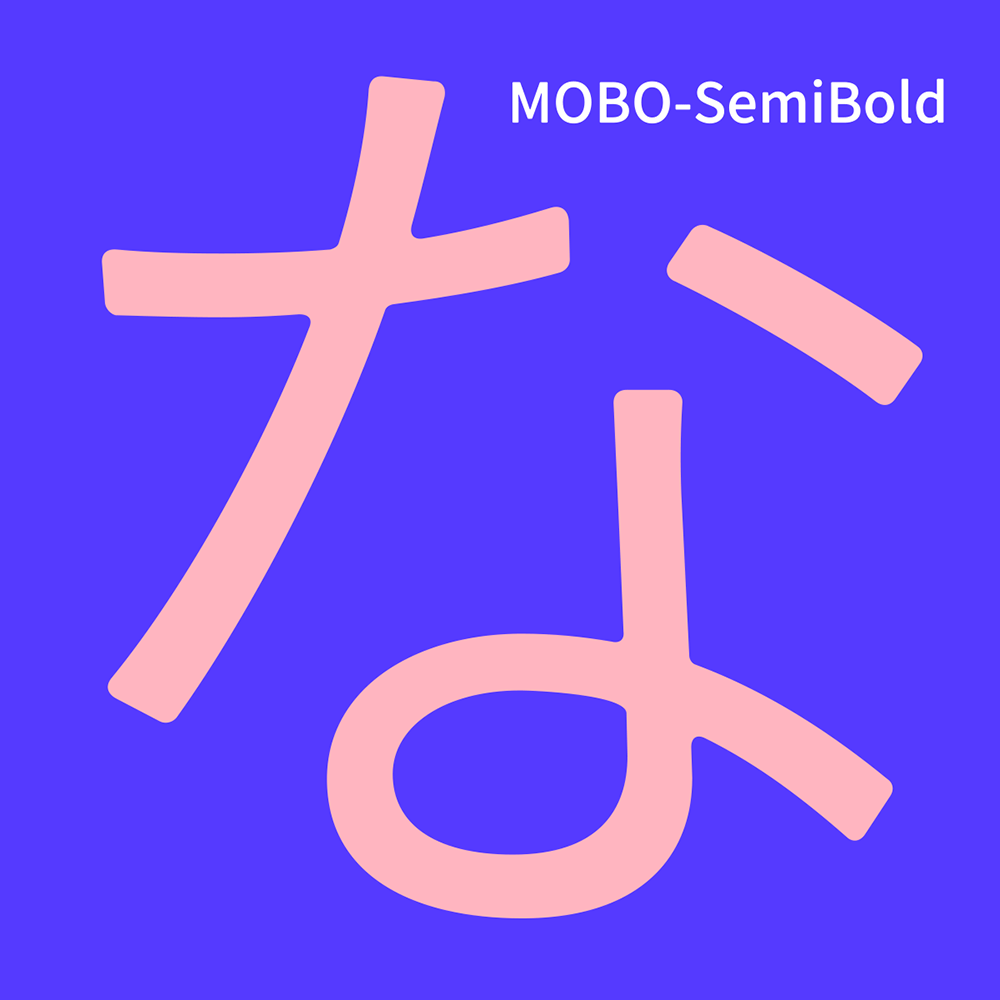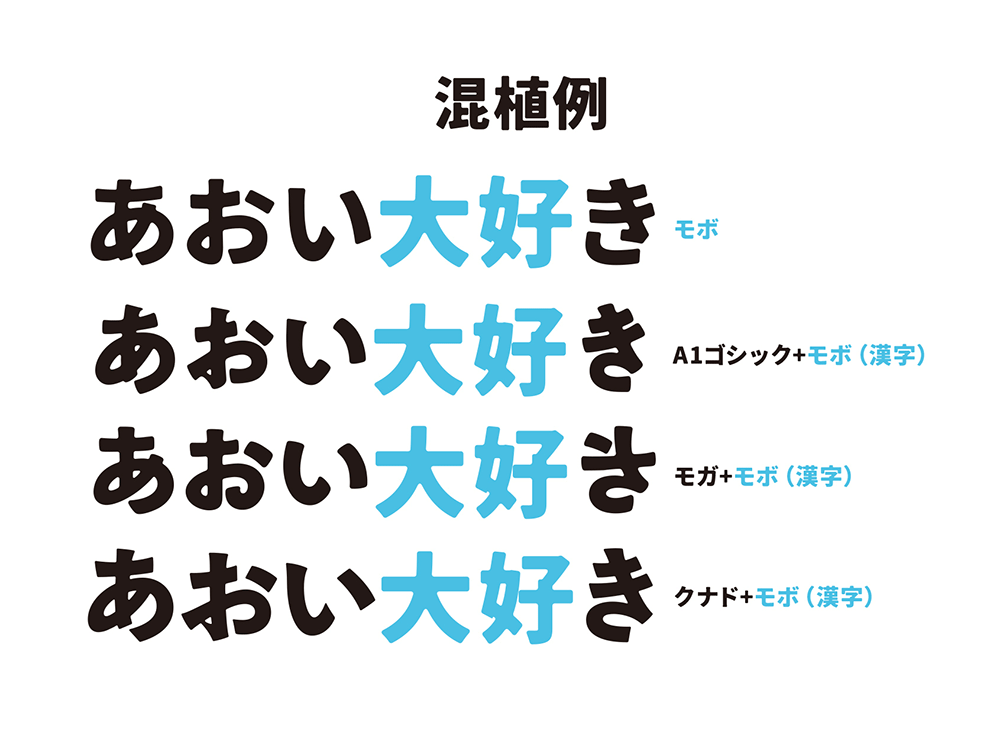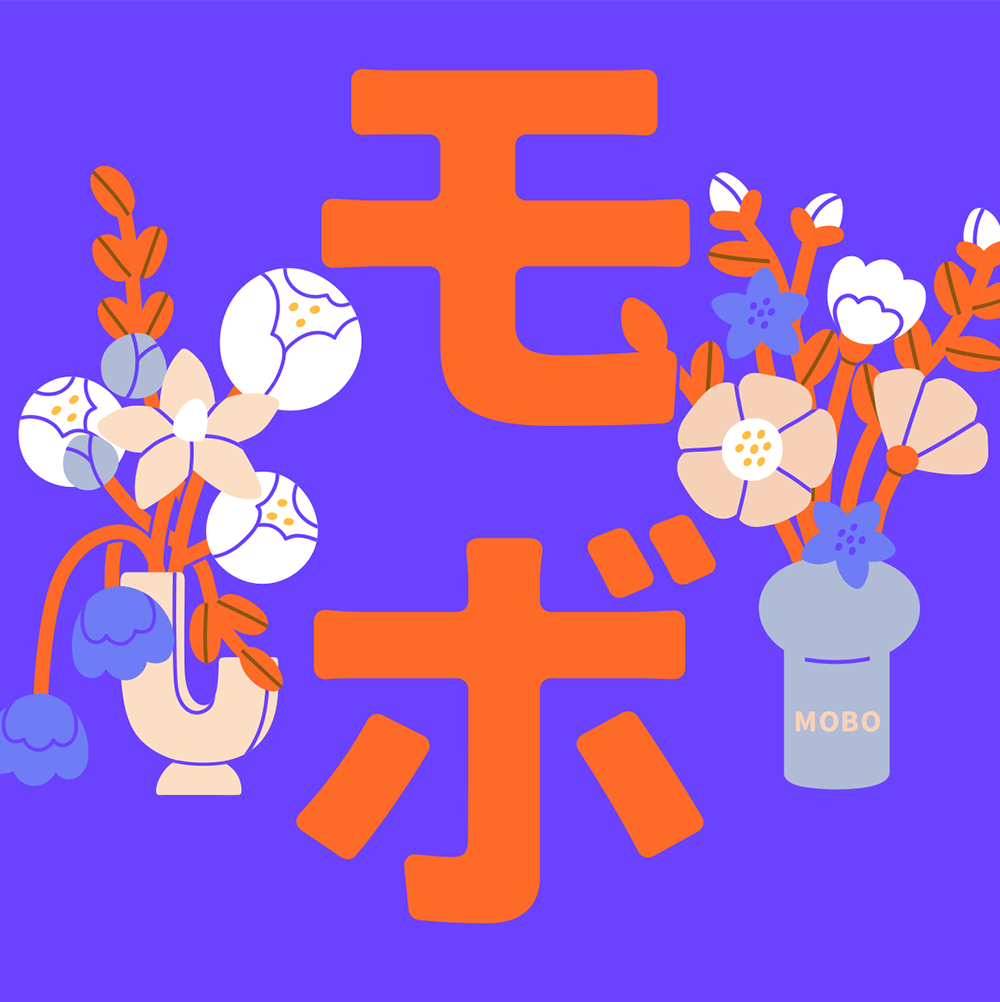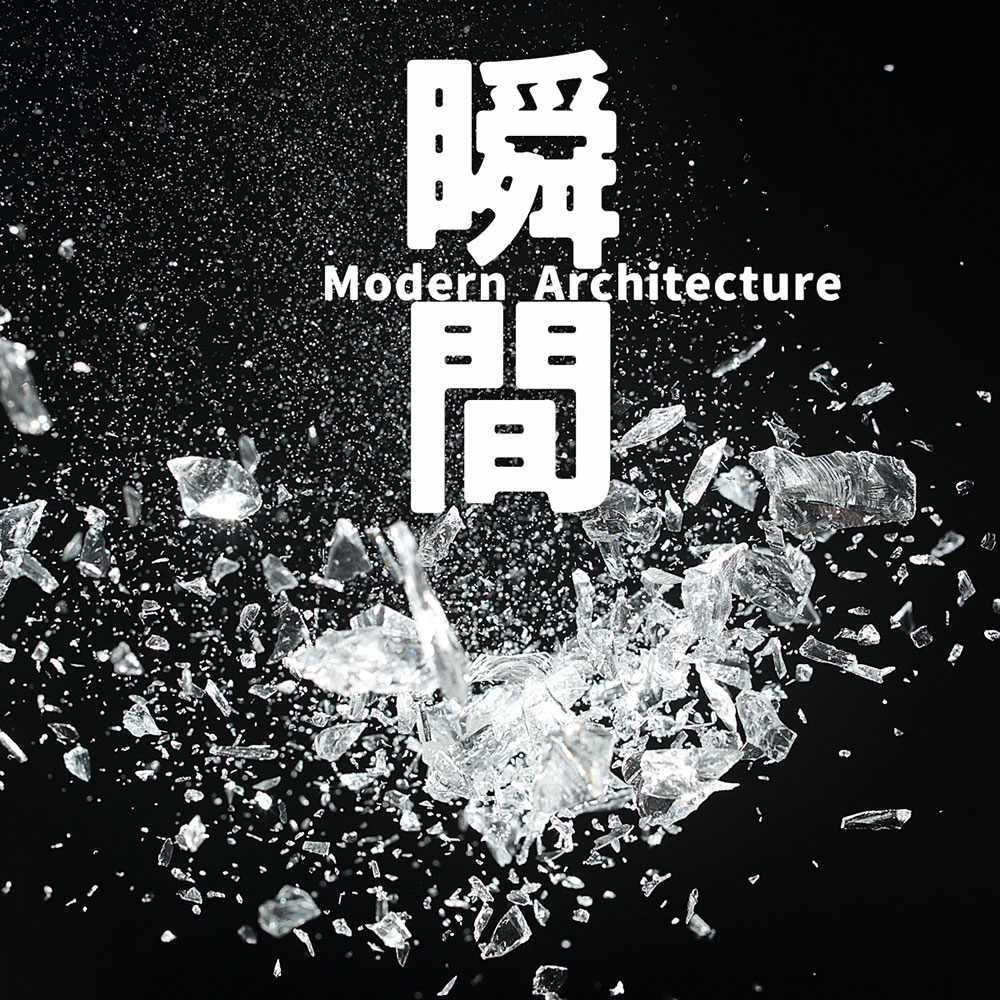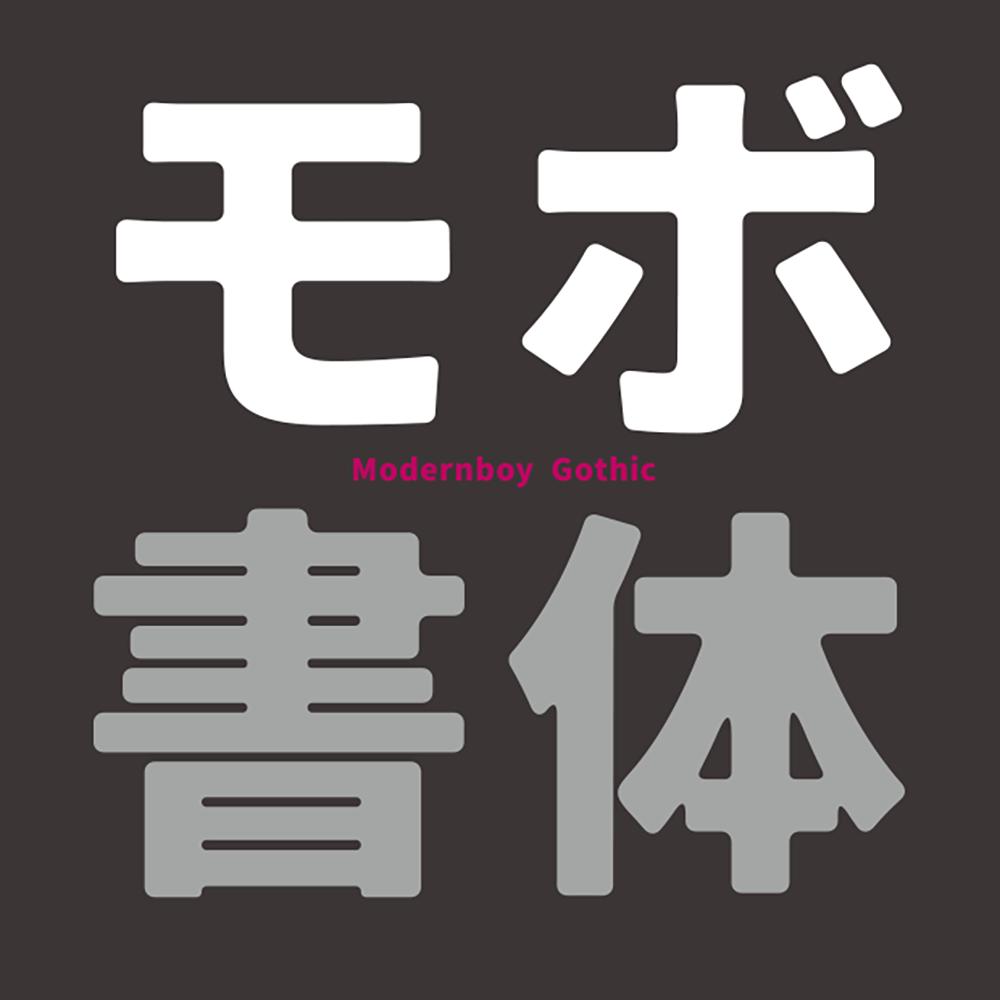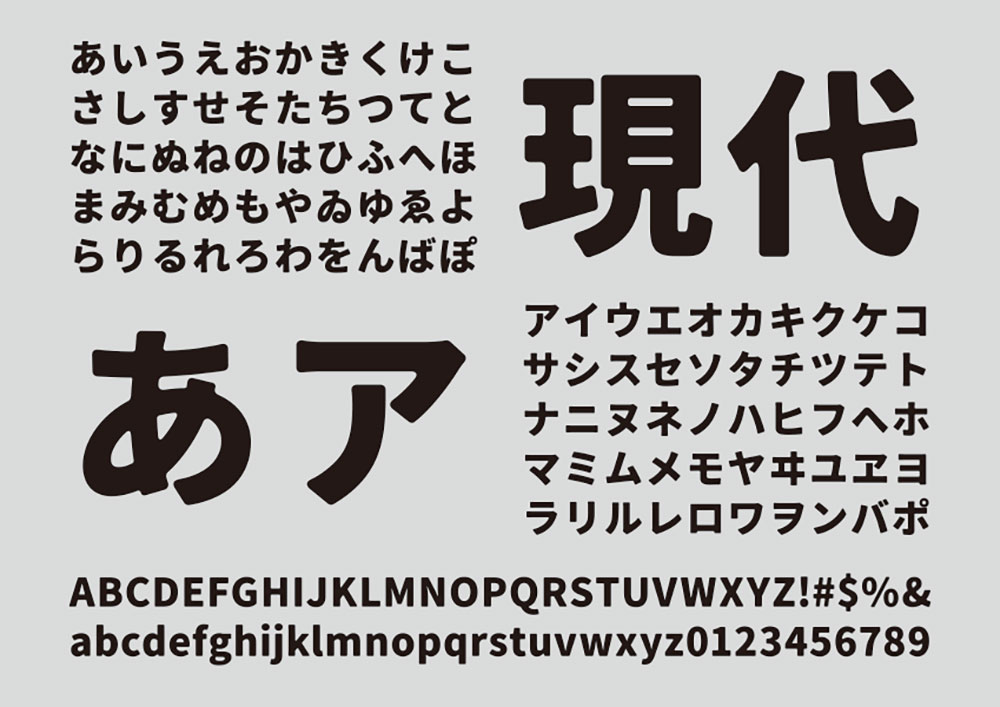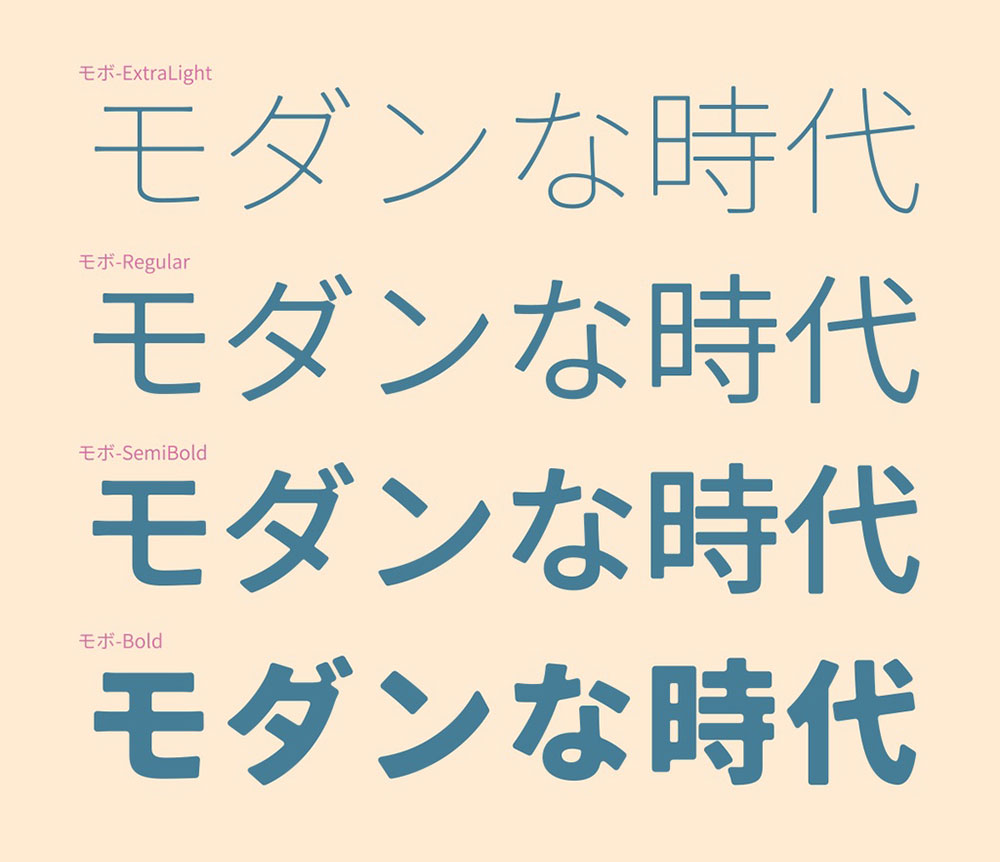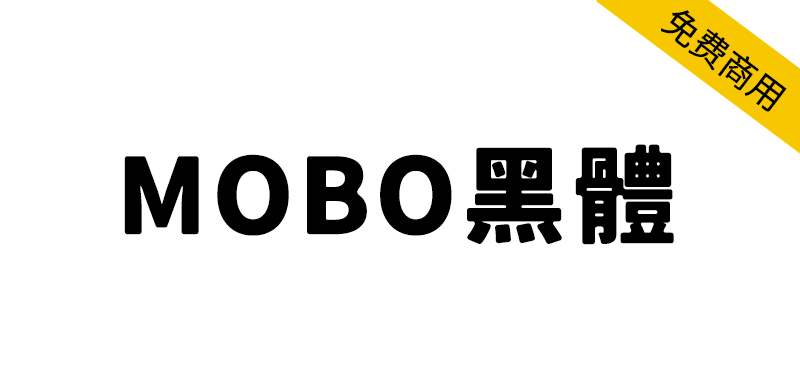
谁说黑体只能硬朗犀利?MOBO黑体偏要打破常规!它以思源黑体为骨架,通过精妙的圆角处理,赋予其前所未有的温柔与复古感。从极细到粗体,四种字重的设计独具匠心,外部圆角随字重变化,内部则保持克制以确保易读性。这款包含海量字符集的日系字体,不仅免费开源,更将为你的设计带来全新的视觉可能。
MOBO黑体(モボ)是一款基于现代黑体骨架字体「思源黑体」通过圆角处理使其呈现柔和复古风格,内含8000字以上的字符集,本字体为开源免费字体。
字重:提供 Bold(粗体)、SemiBold(半粗体)、Regular(常规体)、ExtraLight(超细体) 四种字重。字重越粗,圆角处理越明显,但内部笔画(如转折处)的圆角则保持克制,确保易读性。